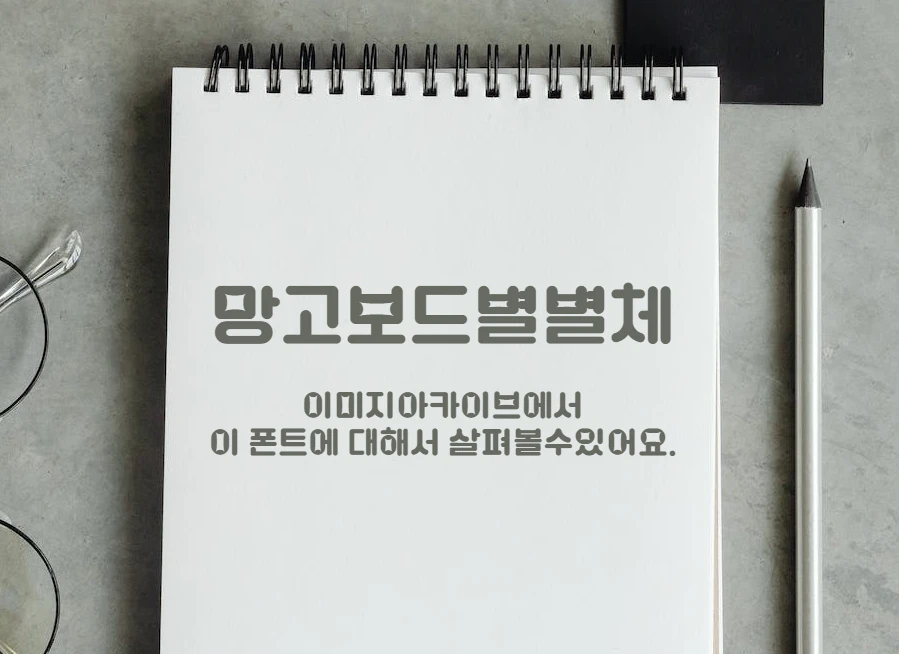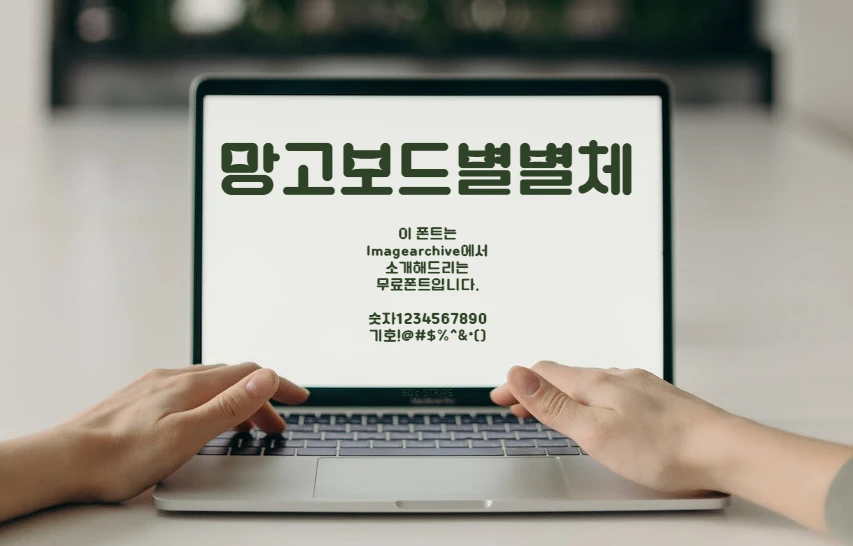
망고보드 별별체
별처럼 빛나는 디자인을 완성시켜줄 망고보드 별별체입니다. 특정 초성에 별빛을 표현하는 아이덴티티를 표현해주었고 망고의 통통하고 부드러운 모양의 느낌을 전해주기위해 획을 부드럽게 표현하였습니다. 별빛이 표현되어있는 초성이 다른폰트와 차별화되는 이 폰트만의 매력을 전해줍니다.